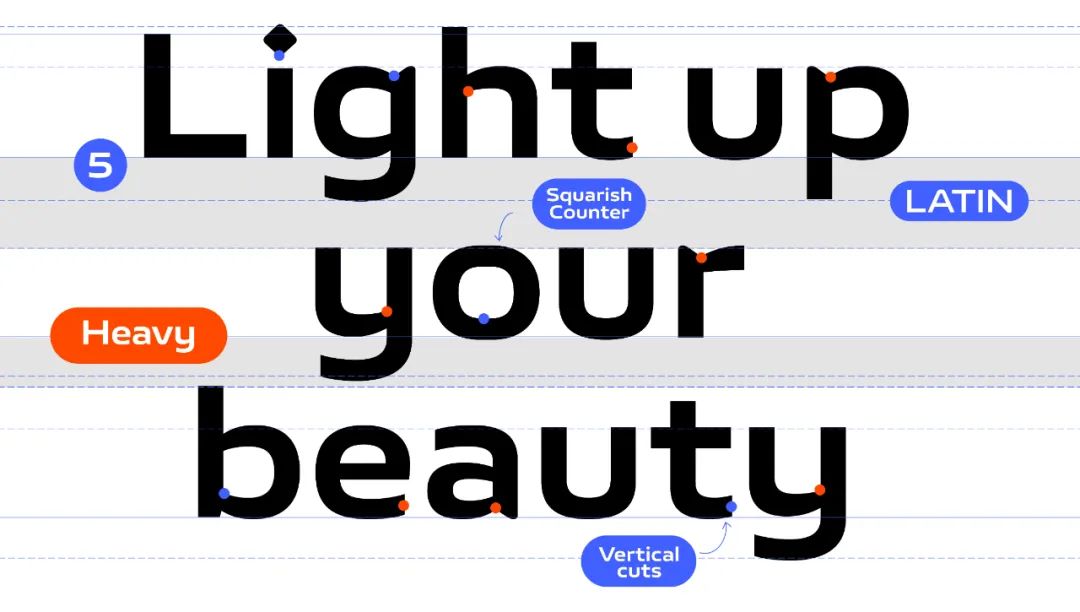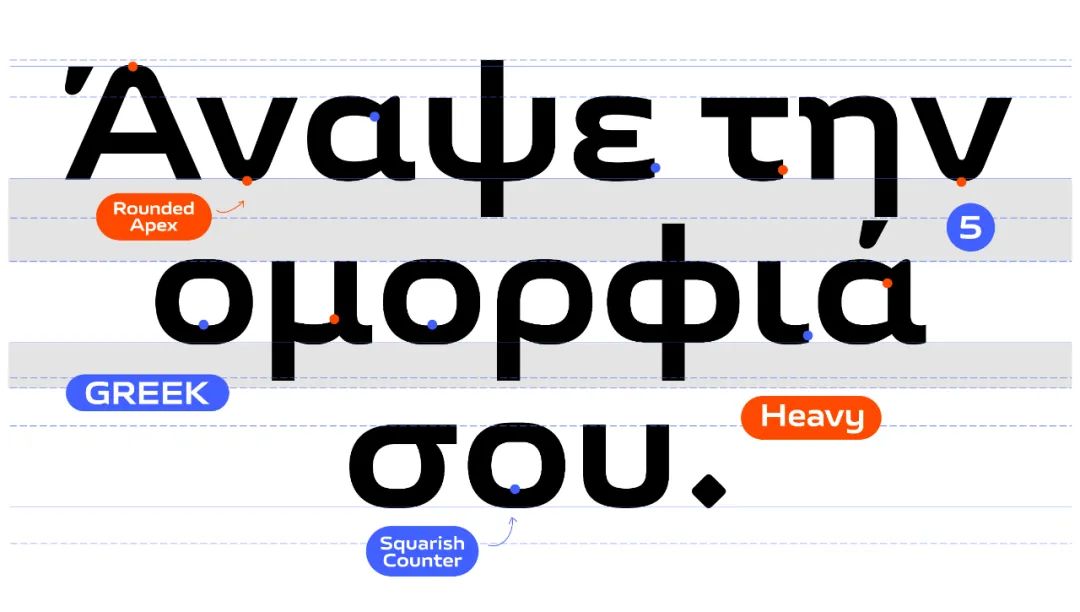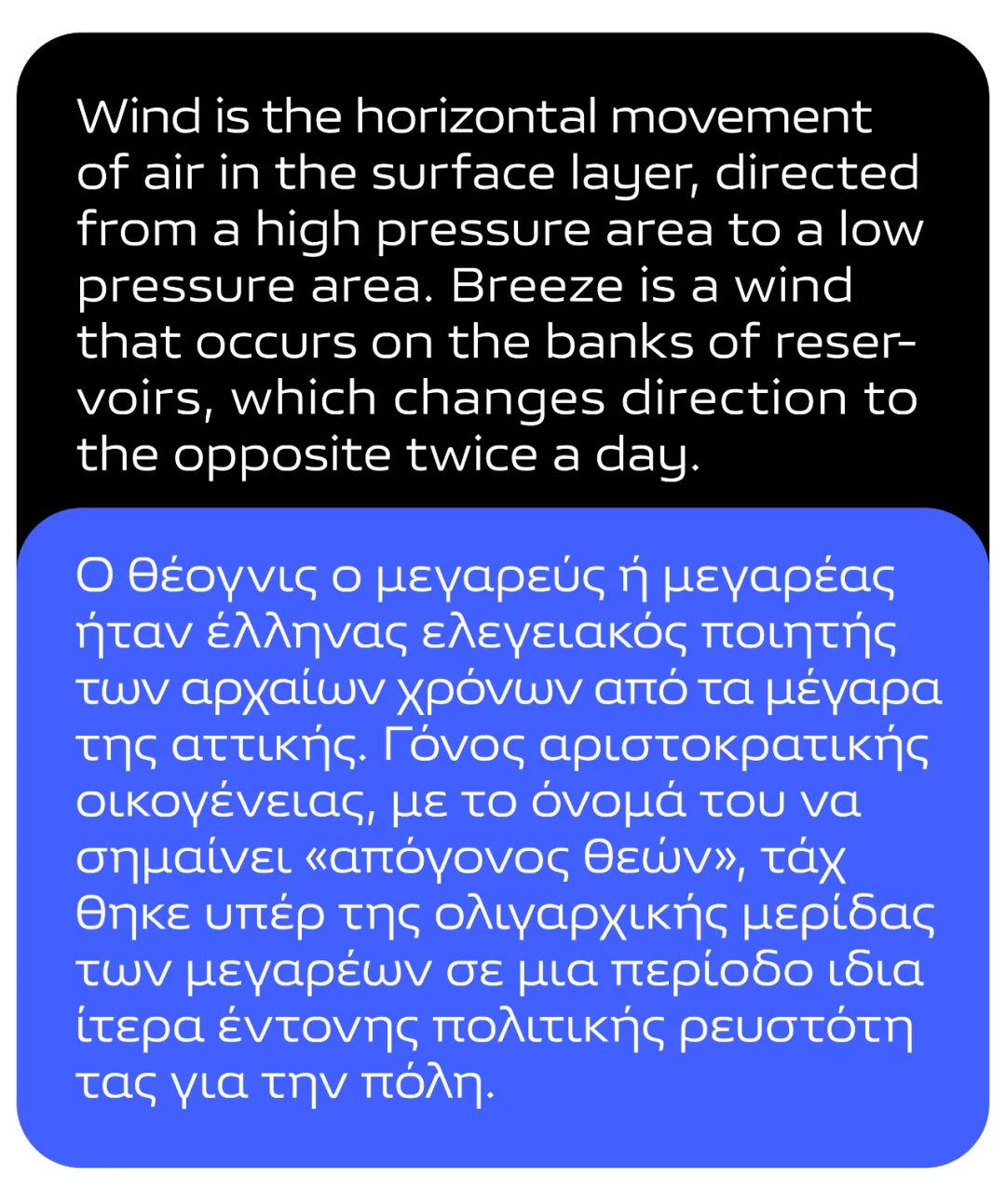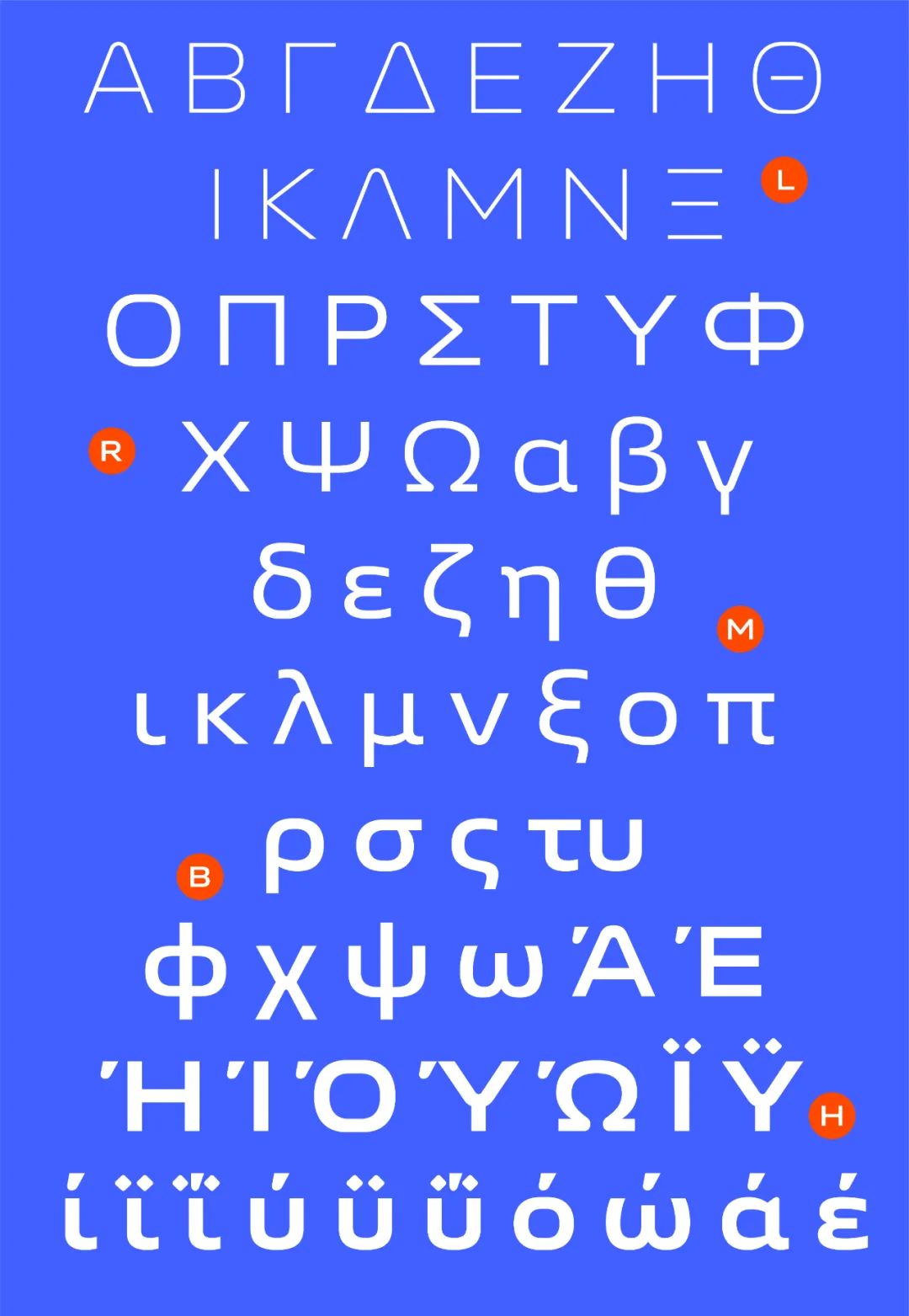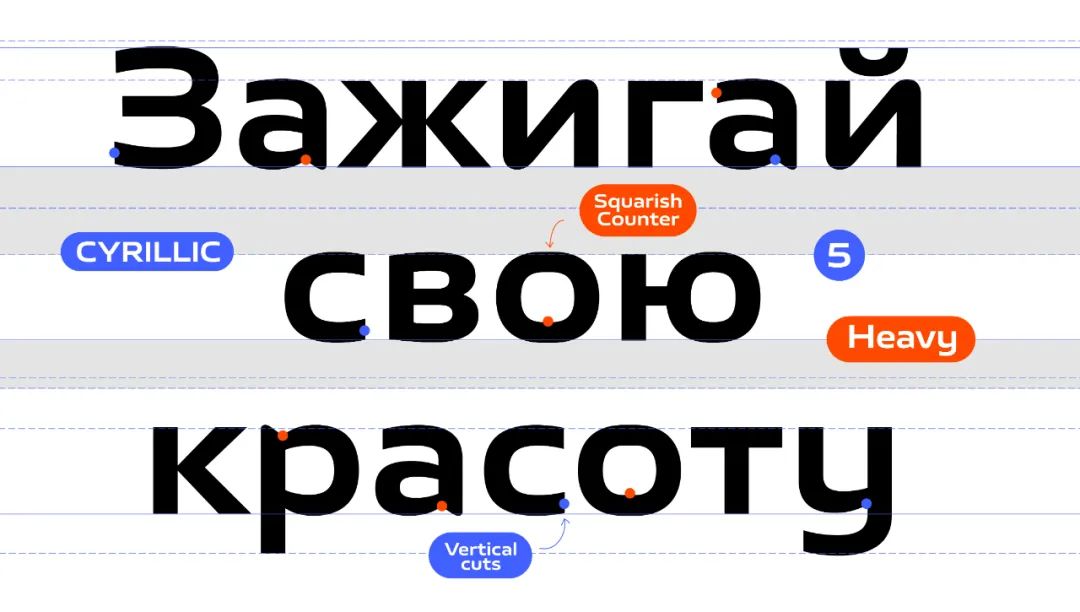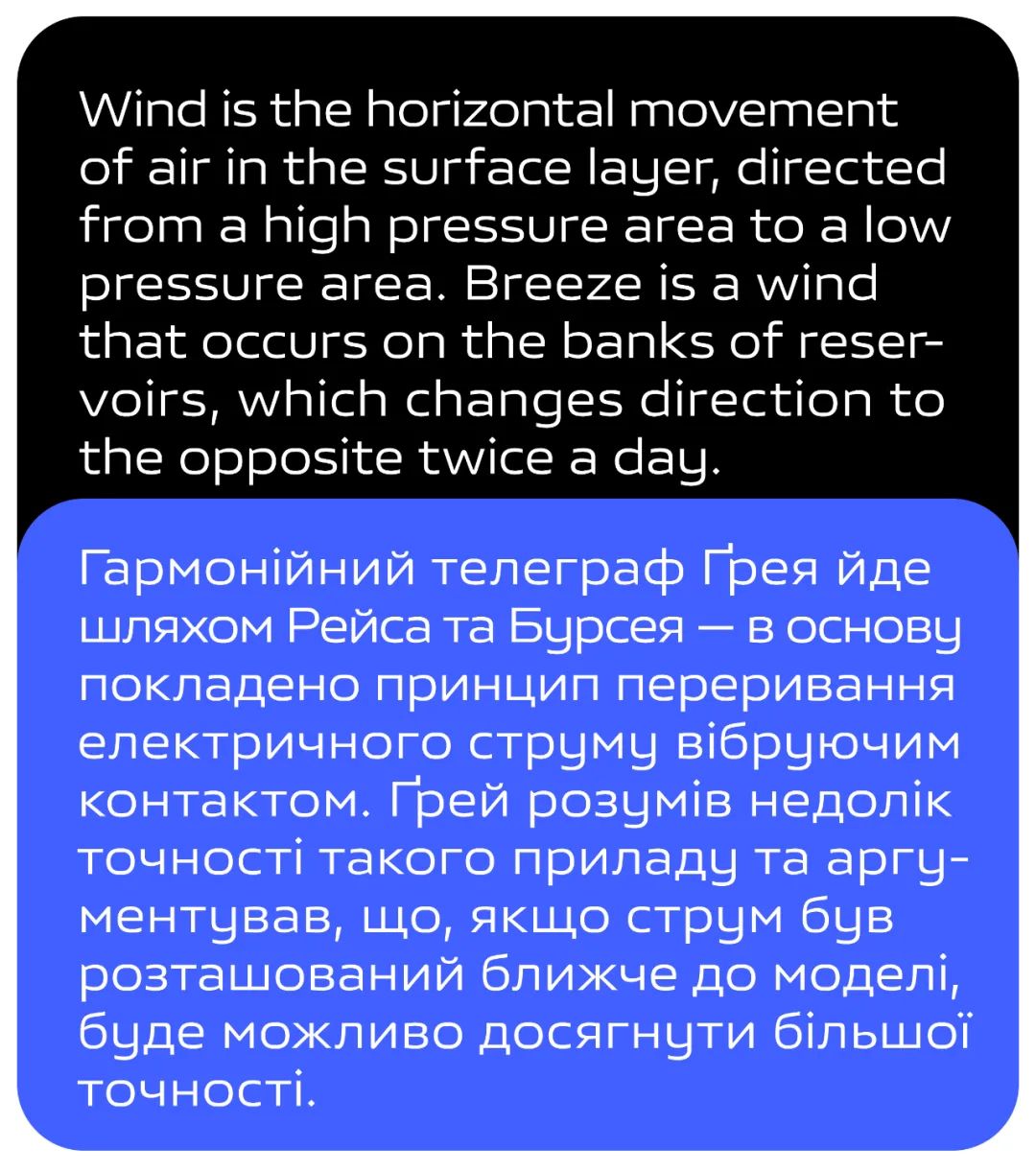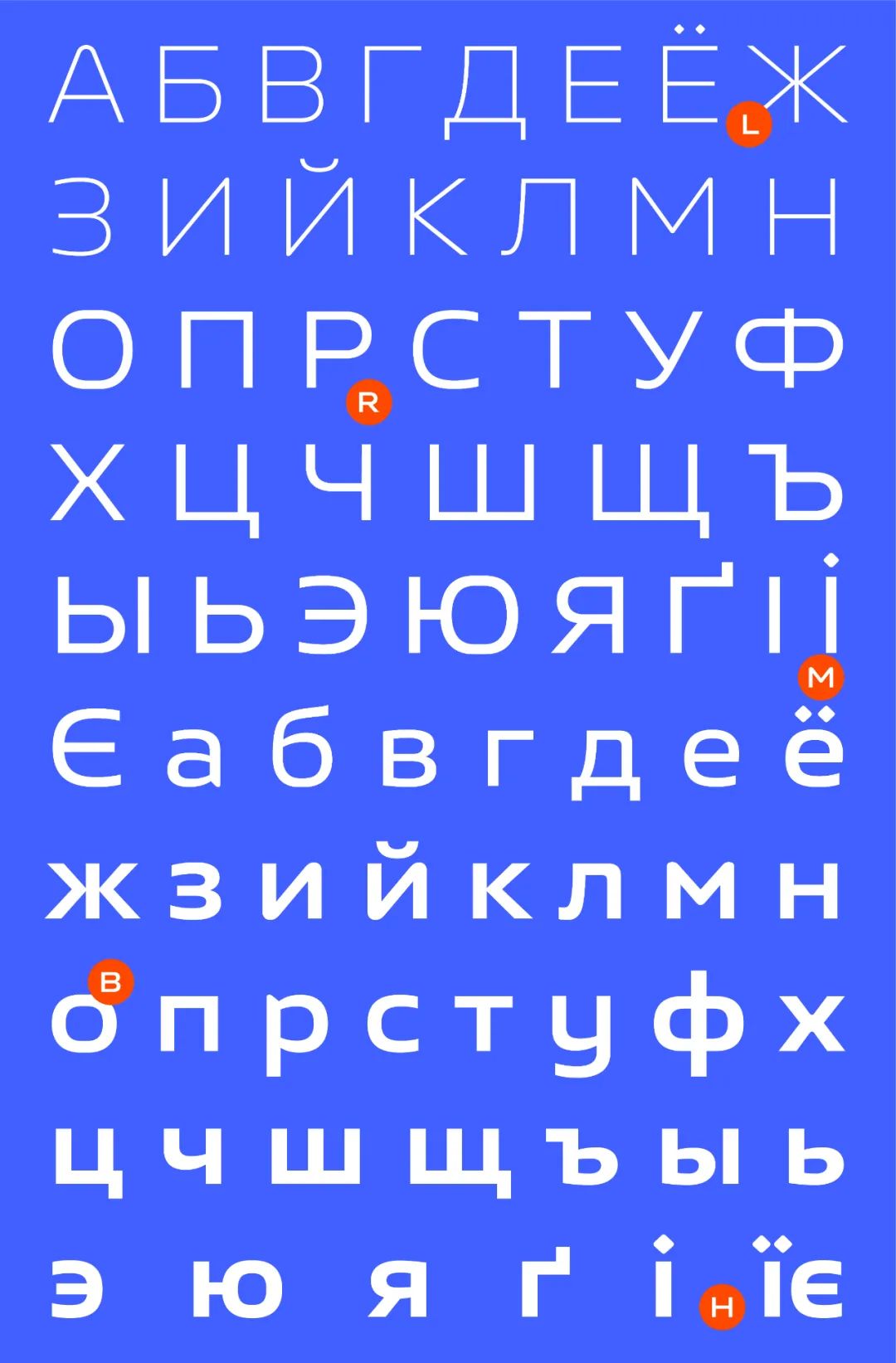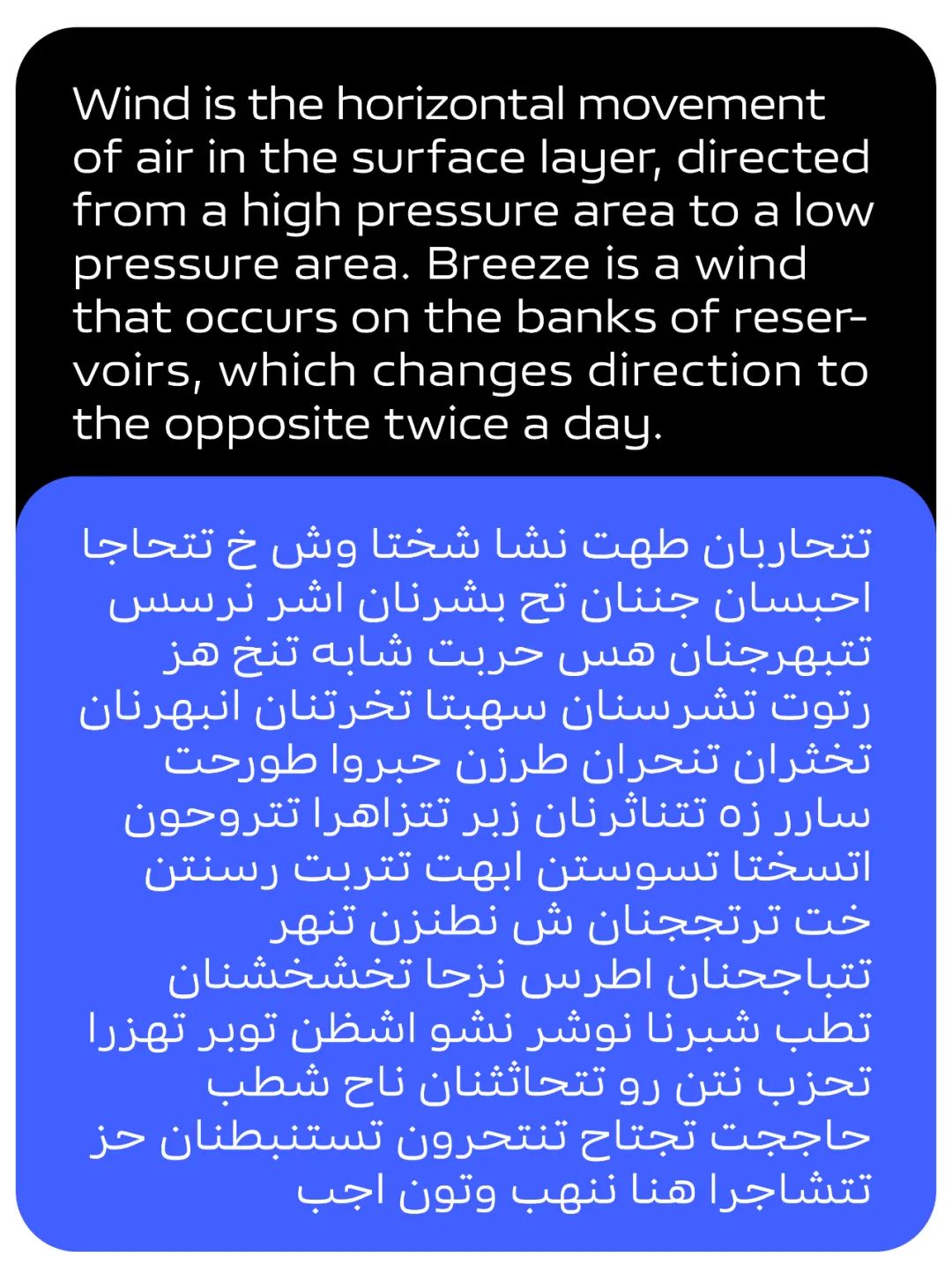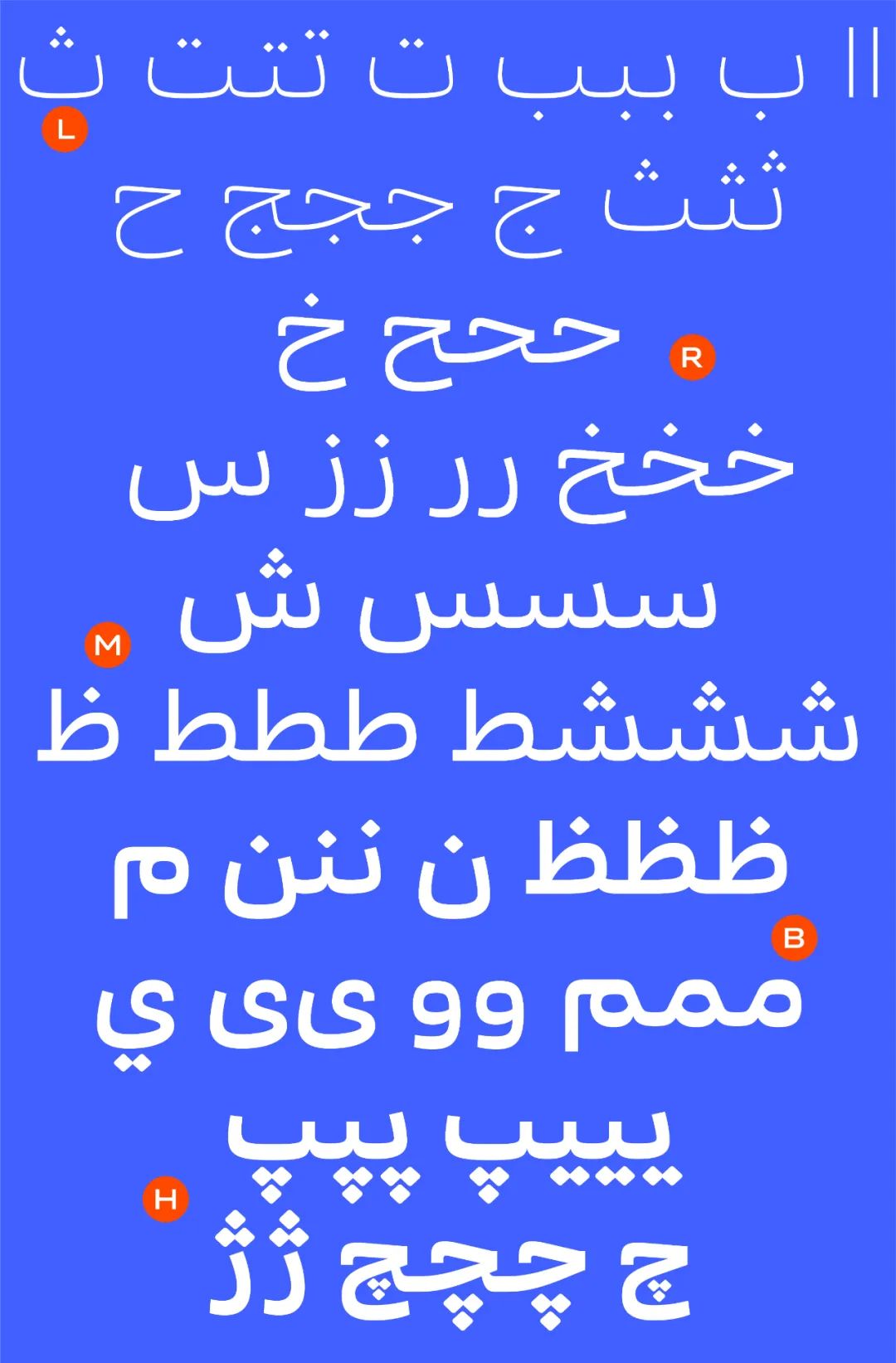
2019年,知名手机品牌vivo在中国市场启用全新升级的品牌视觉形象。作为vivo 品牌焕新的重要组成部分,由丹麦国宝级设计大师BO Linnemann(博·林纳曼)与方正字库联手为其打造的品牌字体——vivo Type,以其鲜明、独特的视觉语言,展现vivo品牌专属的科技感与年轻时尚态。
通过观察、研究,Typetogether 联合创始人José Scaglione 先生归纳出vivo Type 拉丁字符的总体设计风格与细节设计特点,并将其应用在其他3类小语种字符设计中。
vivo Type 拉丁字符
vivo Type的拉丁字符没有采用纯粹的几何外形。其字身结构宽扁、中宫开阔,这一点在粗体中体现得尤为明显;字怀呈方型形状,三角形字符的连接处进行倒圆和去锐处理,字肩与字脚塑造成特别的斜角造型,笔画末端采用垂直切割,在拥有科技感的同时又充分加入人文主义关怀。
vivo Type 拉丁字符特点展示
此次vivo Type的3款小语种拓展字符以拉丁字符为风格坐标,对线条粗细、顶点造型、笔画连接处、笔画末端各处进行了细致的处理,通过加宽字身比例、将字怀变圆为方的形式,来增加字符的年轻化和时尚感,不仅形成了协调统一的设计美感,还保持了vivo品牌整体的视觉风格特点。3款小语种字符均包含Light、Regular、Medium、Bold、Heavy 5个字重,以更好匹配多层级信息设计的需求。
vivo Type的希腊语字符延续了拉丁字符的“折中”风格,字形采用宽体比例,字怀饱满开阔,通过将拉丁字符的入笔和出笔特点融入希腊语中,来传递一致的视觉感受。
vivo Type 希腊语字符(Heavy)
vivo Type 拉丁字符与希腊语字符的匹配
从细节上看,希腊语采用了与拉丁字符一样的水平笔画设计和垂直切口方式,拉丁字符字尾处的直线切割,成为希腊字符引入和引出笔画的灵感来源。同时,希腊语保留了对角型拉丁字母的顶部连接点设计方式,这样的人文主义细节串联起希腊语和拉丁语的视觉共性。
vivo Type 希腊语字符设计细节
vivo Type 希腊语字符多字重展示
vivo Type 西里尔字符同样沿用了拉丁文兼具科技感与人文属性的字符特征,在大写字高、x字高、升部、降部、过冲量(Overshoot)等字符数值的设置上,二者保持完全一致,因而视觉上看,vivo Type的西里尔字符基本还原了拉丁字符的视觉风格。
vivo Type 西里尔字符(Heavy)
vivo Type 拉丁字符与西里尔字符的匹配
除了还原拉丁文的字符尺寸,西里尔字符也在许多细微之处表达着vivo Type 惯有的风格特点:字符水平方向的笔画曲线被拉平,字腔呈现扁平的几何形状;字符连接处的线条采用了适当的粗细对比,防止笔画黏连,具有一定的可读性;字肩和字脚处的三角造型与拉丁字符如出一辙。
vivo Type 西里尔字符设计细节
vivo Type 西里尔字符多字重展示
在vivo Type阿拉伯语字符的设计中,José Scaglione 先生发现,最能与拉丁字符匹配的阿拉伯语字体是Naskh,这款字体结构简单,字身比例宽大,线条粗细变化不明显,字怀充盈饱满。
vivo Type 阿拉伯语字符(Heavy)
vivo Type 拉丁字符与阿拉伯语字符的匹配
Naskh的阿拉伯字母Alef 线条笔直,无粗细变化,切角处采用干脆的水平切割方式;字母Waw 将传统的三角形字腔变化为方形;字母hah 模仿拉丁字符的结构,主体更偏矩形,而不是传统的圆形构造,其点的形状则与拉丁字符的点完全一致。
vivo Type 阿拉伯语字符设计细节
vivo Type 阿拉伯语字符多字重展示
至此,vivo Type成为一款涵盖中文、拉丁文、希腊语、西里尔语、阿拉伯语5个不同语种的超级定制字体家族。多语种间的风格呼应与字符匹配,确保了vivo Type在不同国家和地区的广泛适用性,具有更加长久的生命周期和深远的影响力。
升级后的vivo Type在展现vivo固有的科技感与人文关怀属性的同时,能够助力品牌实现在全球市场的乘风破浪。
vivo Type 阿拉伯语与西里尔语在vivo品牌中的应用